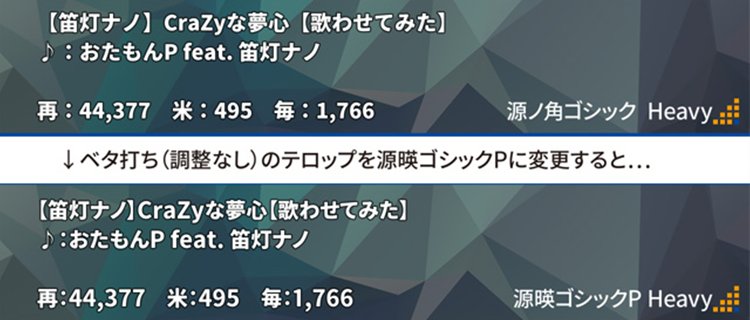
源暎ゴシックは、GoogleとAdobeが共同開発した高品質なオープンソースフォント「源ノ角ゴシック」をベースに、動画のテロップやパワーポイントのスライドなどで使った際に、見栄えがよくなるように改変したゴシック体フォントです。
「源暎ゴシックP」は、文字幅を適度に詰めて、欧文と数字が日本語部分に合わせて大きなサイズになっています。テロップやスライドでそのまま使用しても、文字のバランスが適切になっています。
「源暎ゴシックN」は、文字幅は等幅のままになっており、グリフの改変や欧文、数字の拡大のみが適用されています。
「源暎ゴシックM」は、英数字なども含めて等幅になっています。
「源ノ角ゴシック」と「源暎ゴシックP」の比較